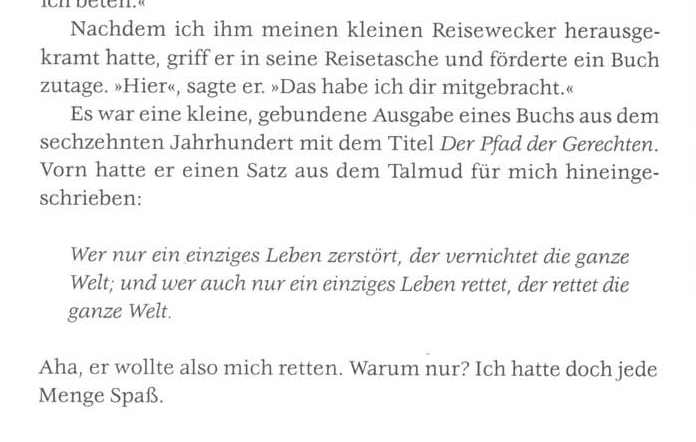
Schrift eines Ullstein-Buches
Ich habe die Schrift schon in mehreren Büchern des Ullstein-Verlages gesehen. Das abgebildete Beispiel ist auch aus einem Ullstein-Buch. Erkennt sie jemand (trotz der schlechten Auflösung)?
Ja, das ist sie! Vielen Dank! :-D Ist das nicht eine tolle Schrift?
Verrate mir nur noch, wie Du das geschafft hast. Ich habe mir zig Leseproben angesehen und alles mögliche gefunden, nur nicht, was ich gesucht habe!
Und da war sie dann irgendwann, die Veljovic :-D
Edit: Von Elsner+Flake gibt es die Veljovic auch mit Mediävalziffern; leider fehlen die Kapitälchen.